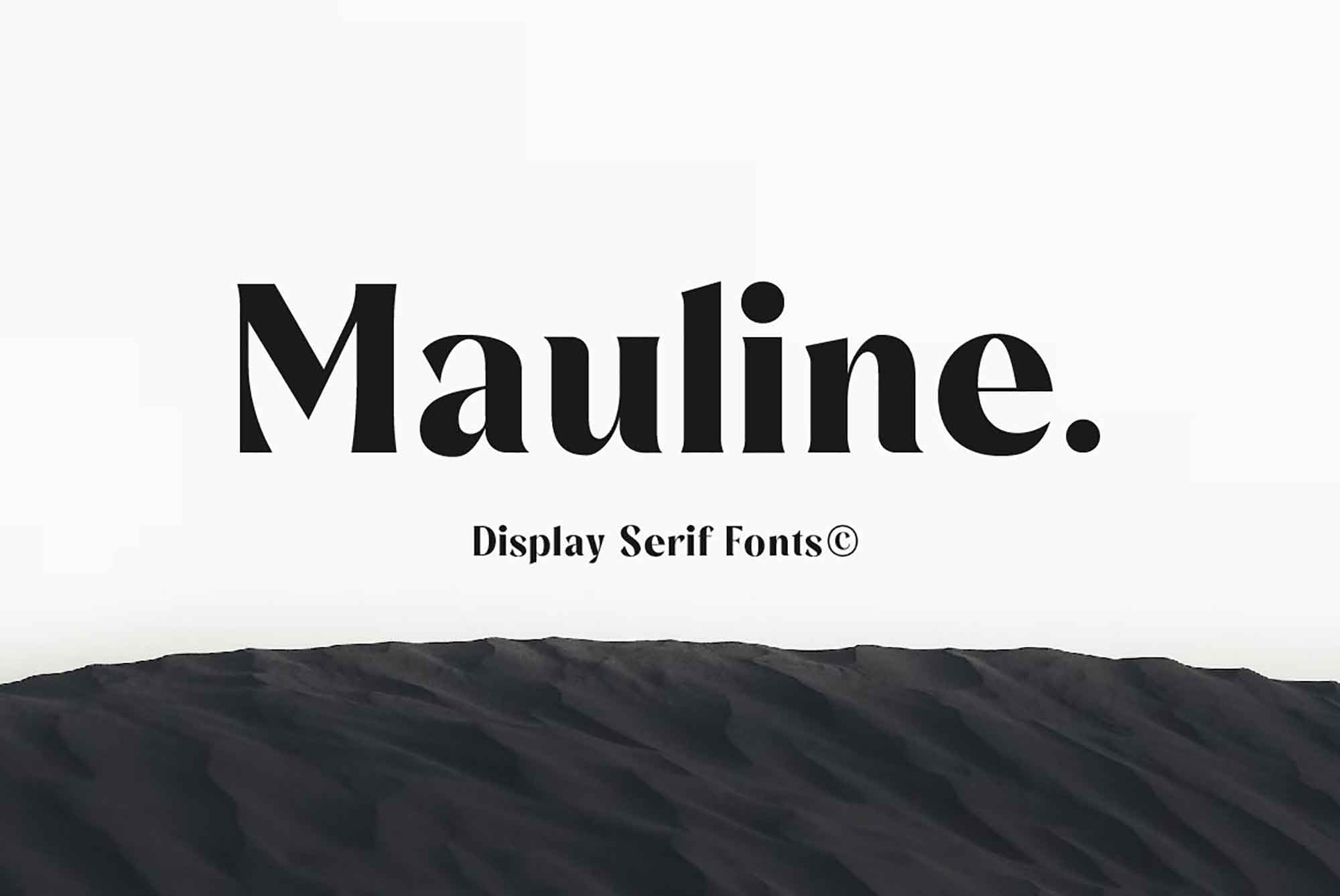
Mauline Display Serif Font – Download Grátis
A fonte Mauline Display Serif é um deslumbrante recurso gráfico ideal para quem busca uma mistura harmônica entre elegância e modernidade. Seu design delicado e seus traços sóbrios permitem criar design inovadores e impactantes. Esta fonte, criada pela Yukita Creative, é especialmente versátil, atendendo tanto às seções de cabeçalho quanto ao texto do corpo do documento. Suas linhas claras e suaves se sobressaem em qualquer projeto, criando uma atmosfera gráfica envolvente que remete à cultura e ao estilo do Brasil. Seja para projetos de jornalismo, design editorial ou design de interface de usuário, a fonte Mauline Display Serif oferece o equilíbrio perfeito entre simplicidade e sofisticação, proporcionando uma experiência de leitura envolvente.